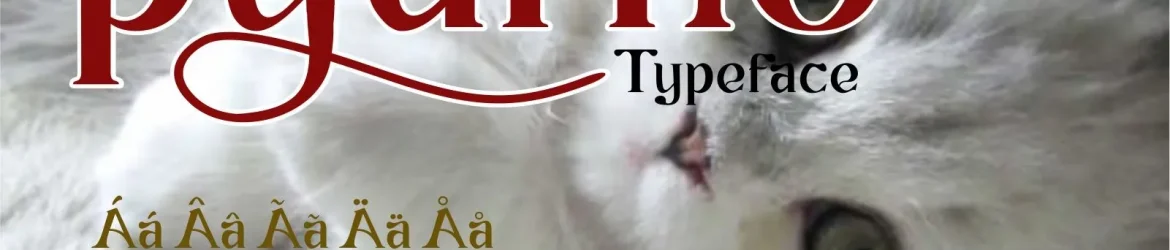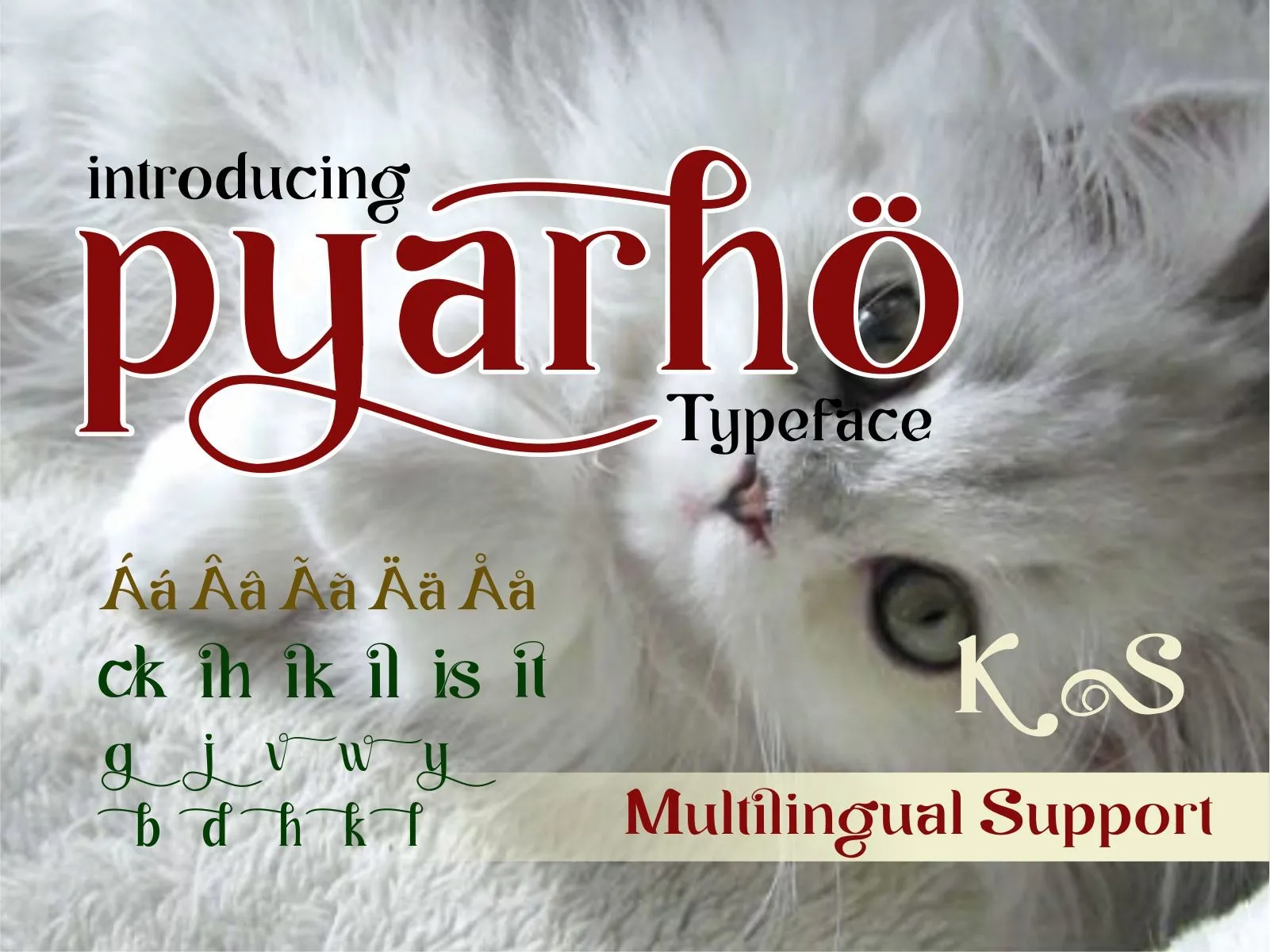
Pyarho Font – Fonte Grátis
Pyarho Font
Esta é uma fonte serif moderna com contornos delicadamente arredondados que adicionam um toque único à sua natureza compacta. Ideal para quem busca um equilíbrio entre elegância e modernidade, esta fonte oferece todos os caracteres e swashes de forma fácil através da codificação PUA. Adicione-a com confiança às suas criações mais especiais e deixe-se encantar pelo resultado impressionante que ela gerará. É uma fonte serif que combina elementos modernos com um charme sofisticado, perfeita para quem busca personalidade em seus projetos visuais.